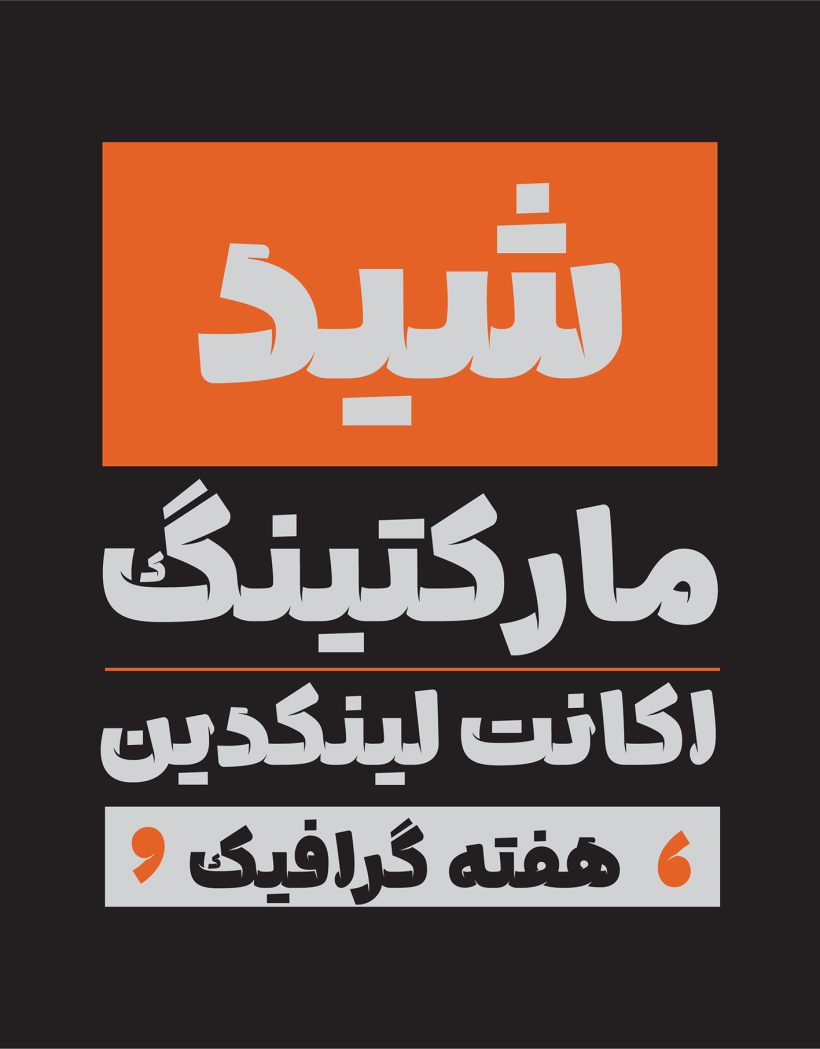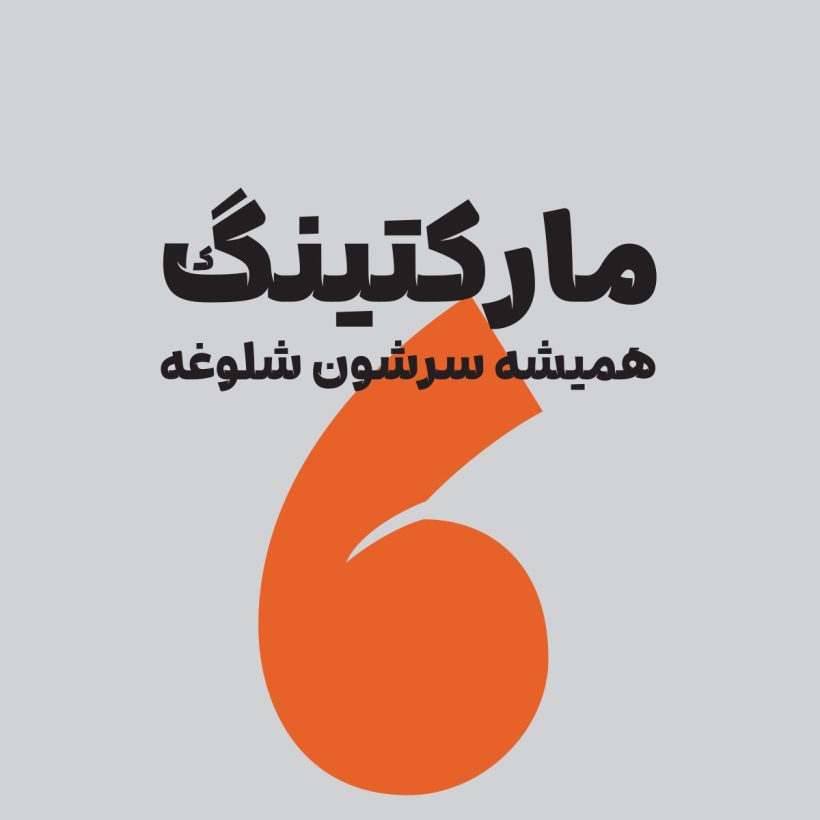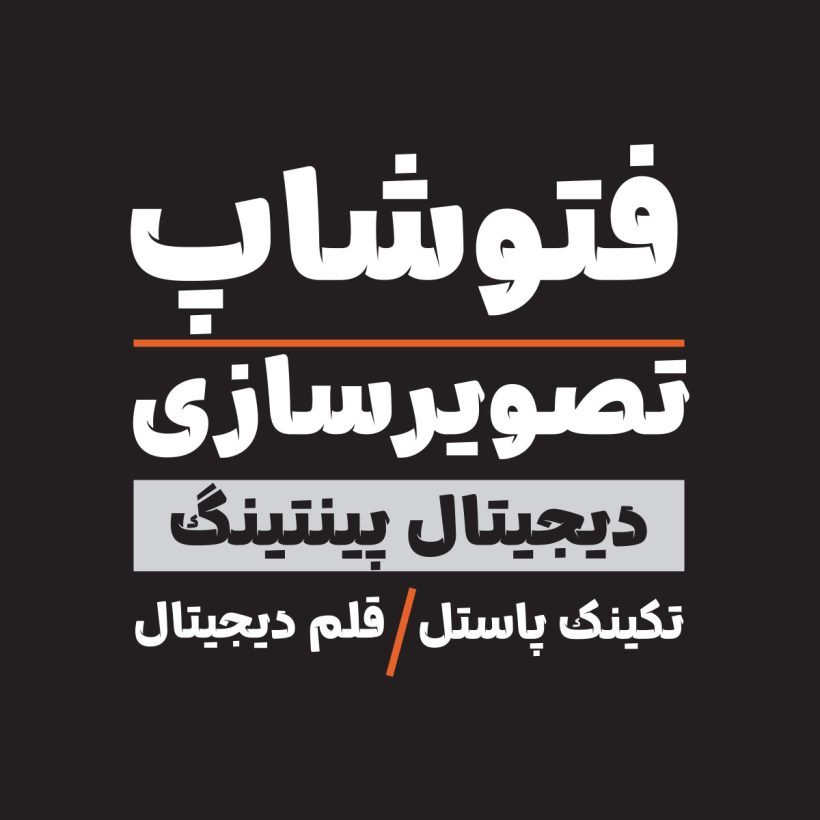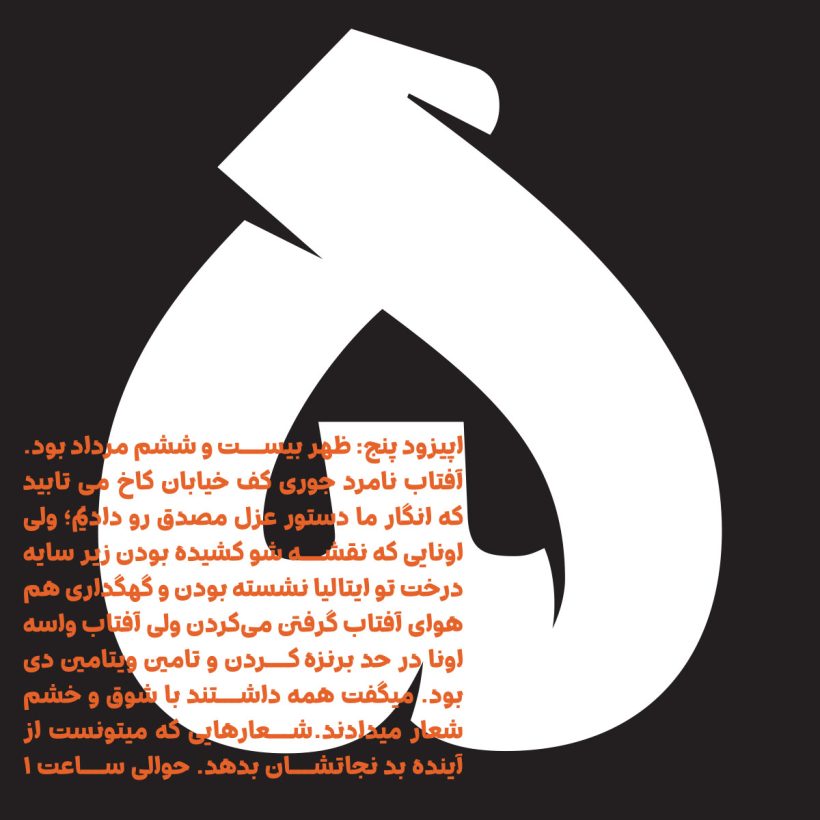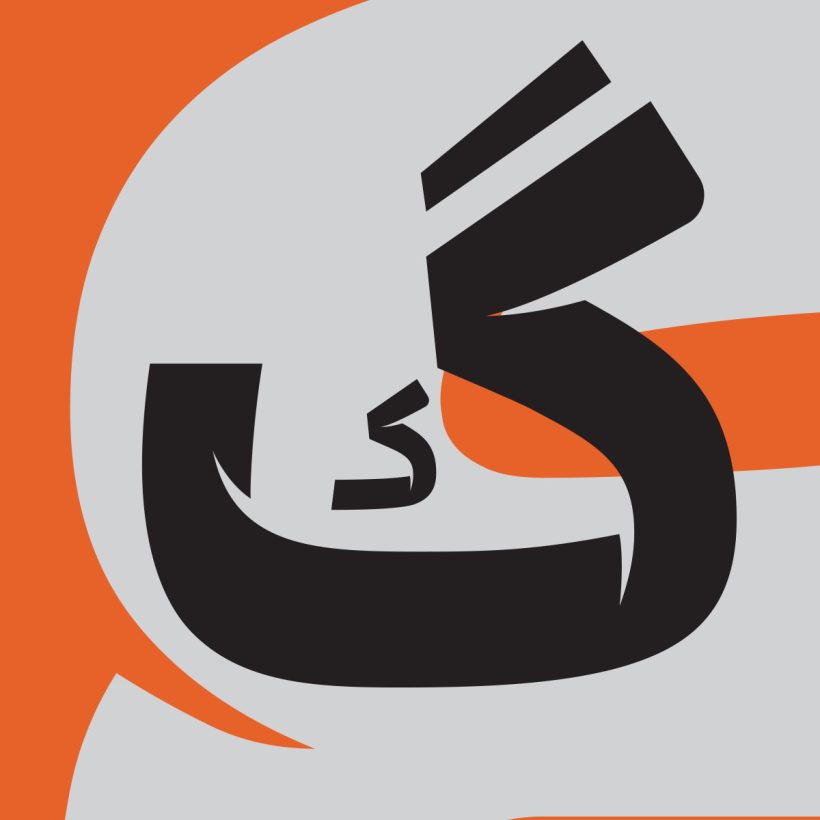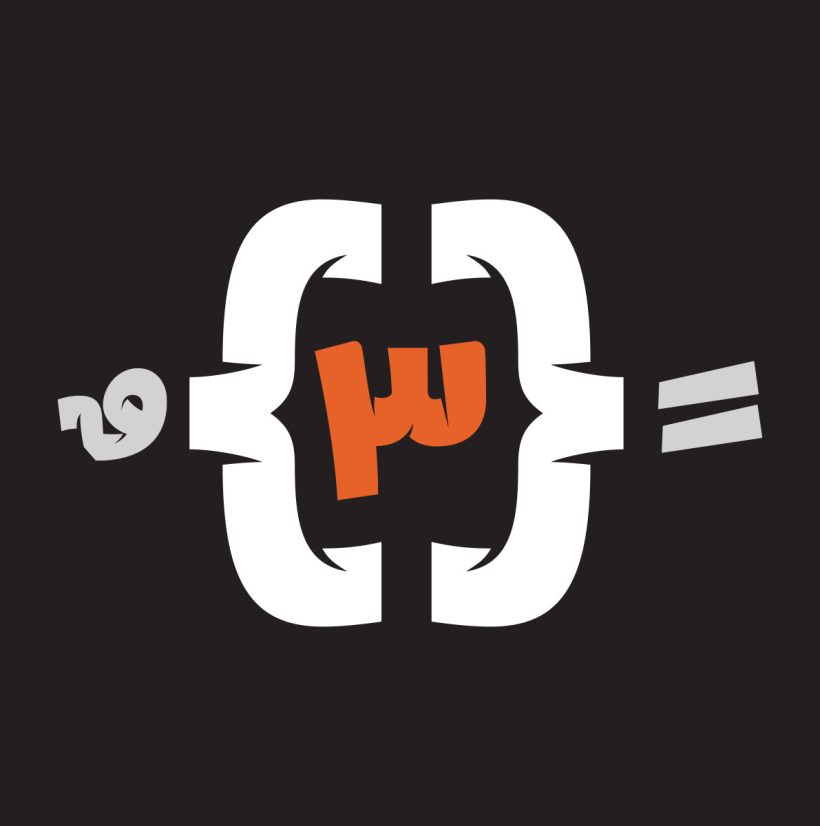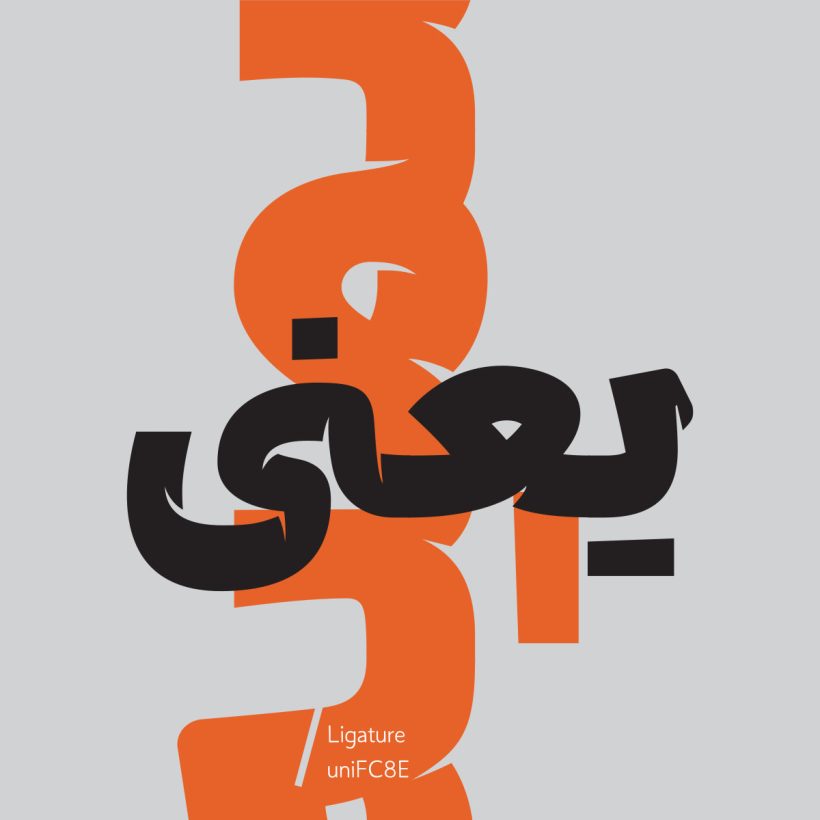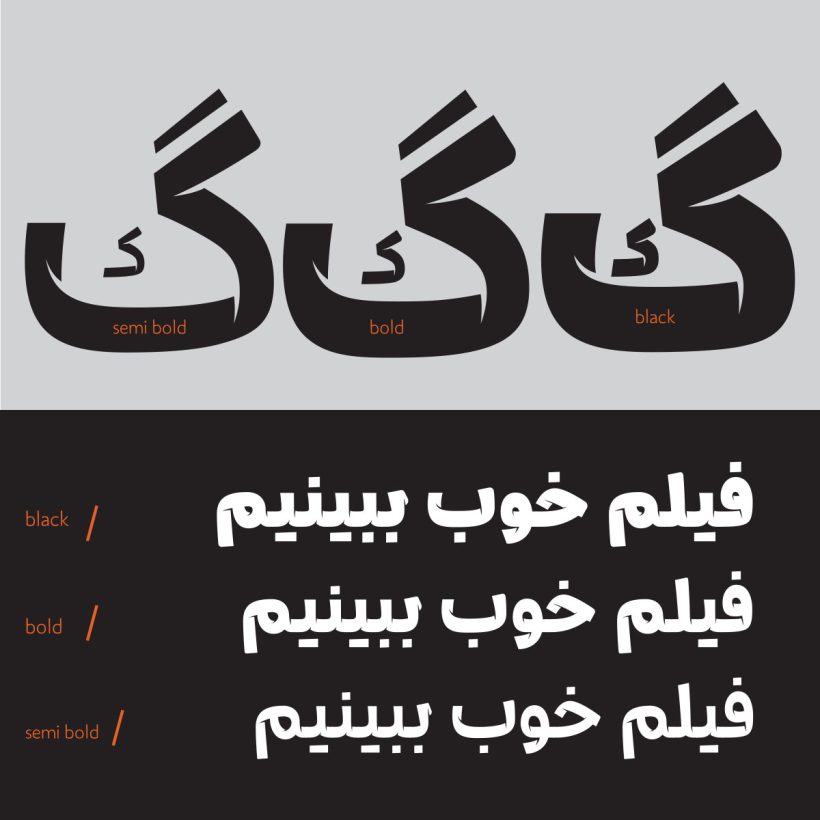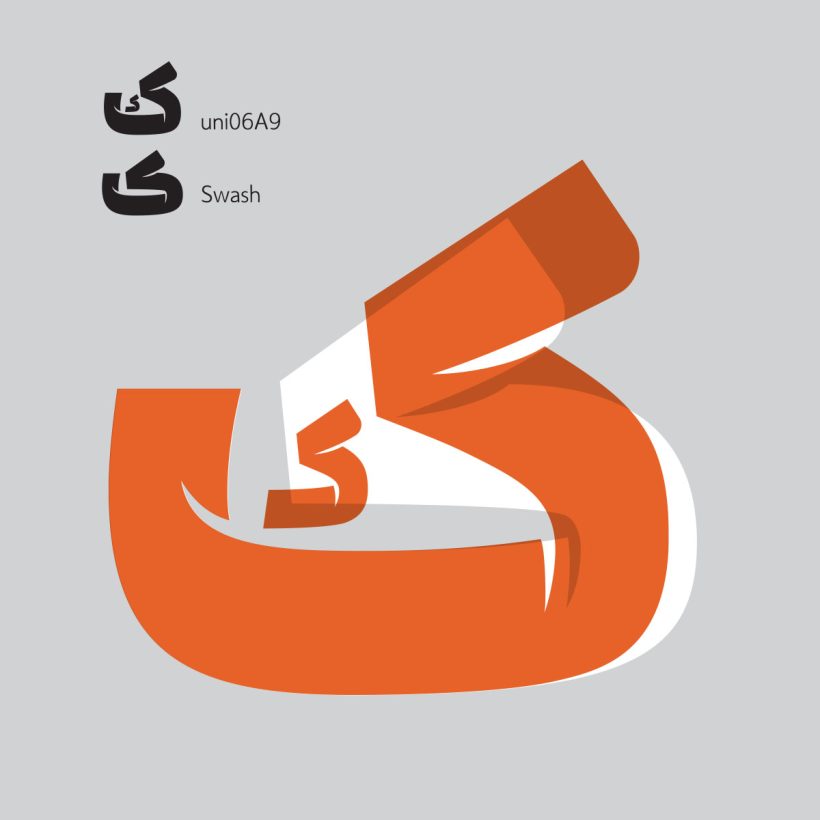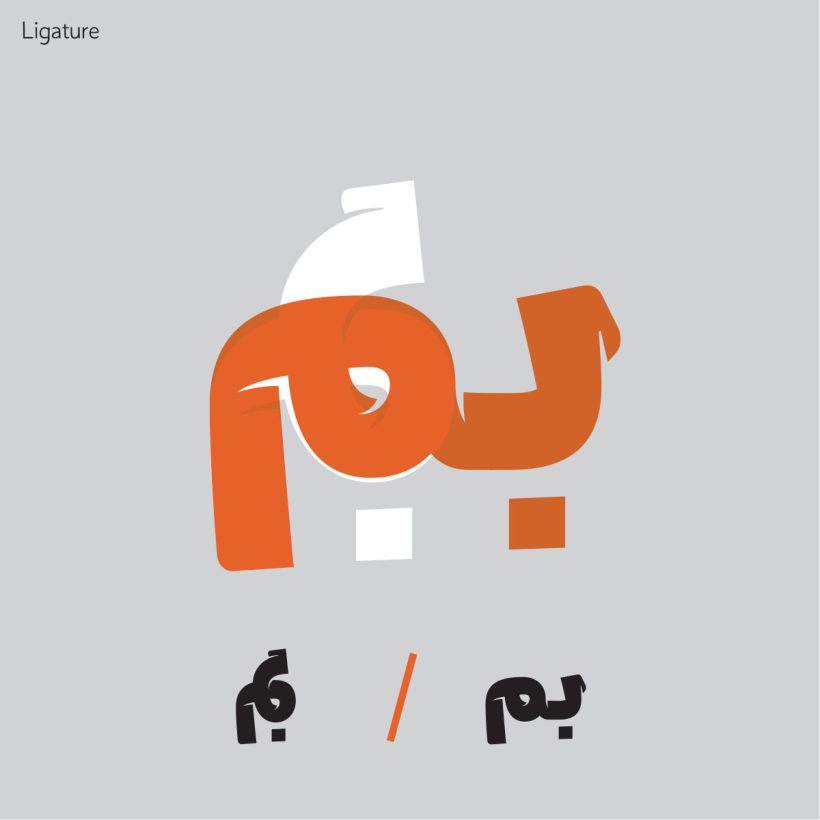
خانواده فونت شید
تایپ فیس نمایشی شـید براساس ساختار کلی خط نسخ و با بازی بصری در فضای مثبت و منفی گردشهای حرکات قلم طراحی شده است. شکافهایی که در تایپفیس شـــید به کار رفته پویایی و انرژی بیشتری در مقایسه با فونتهای کلاسیک مبتنی بر خوشنویسی به آن داده است. از طرف دیگر، میتوان آن را روشی برای پر کردن چالههای مرکب در نظر گرفت. در کاربرد شکافها تا حد ممکن به زیبایی حروف هم توجه شده است. شـید در سه وزن ارائه شده و با وجود اینکه نمایشی است و برای تیتر و عبارتهای کوتاه مناسب است اما وزن نیمه بولد آن در متن کوتاه نیز قابل استفاده است. شــید میتواند برای تولید محتوای کسبوکارها و امور تبلیغاتی مورد استفاده قرار گیرد.
در تولید فونت شید، قواعد کرنینگ و اعرابگذاریها به طور کامل اعمال شده است. همچنین شــید دارای لیگیچر و کارکترهای جایگزین است تا برحسب نیاز و برای زیبایی بیشتر به کار گرفته شود.
شما با خرید فونت شید یک فونت دو زبانه فارسی و عربی خواهید داست.
اعداد فارسی و عربی در فونت شید تنظیم شده و قابل استفاده است.